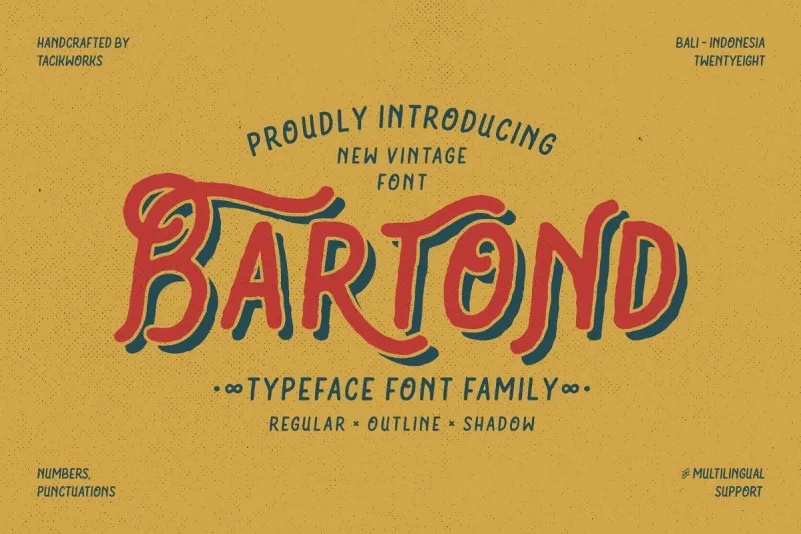
Bartond Typeface – Fonte Grátis
Bartond Typeface
Bartond Typeface é uma fonte tipo display que captura a essência vintage com linhas rúmidas, oferecendo uma versatilidade incrível. Este conjunto de caracteres tem mais de 219 símbolos, incluindo maiusculas e minúsculas, ligaturas discretionary (ou seja, que podem ser usadas opcionalmente para melhorar a legibilidade) e alternativas de ligatura padrão. Esse design foi inspirado por estilos vintage e foi projetado pela Tacikworks. Bartond Typeface é perfeito para criar designs vintage, como logotipos, cartazes, merchandising, brochuras, cartões de visita, ou qualquer outro projeto que busque uma atmosfera nostálgica. Seus traços rúmidos e sua versatilidade combinam perfeitamente com as nuances dos estilos vintage originais, dando a impressão clássica da fonte um toque autêntico do passado. Este design é ideal para quem busca trazer uma atmosfera vintage ao seu próximo projeto visual.